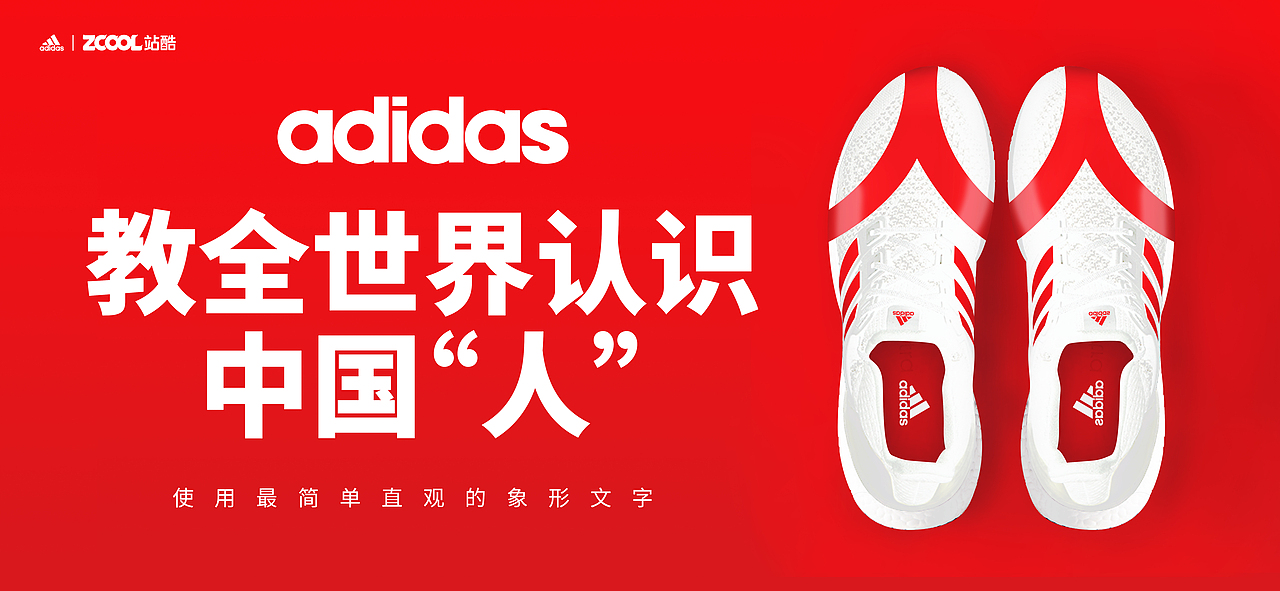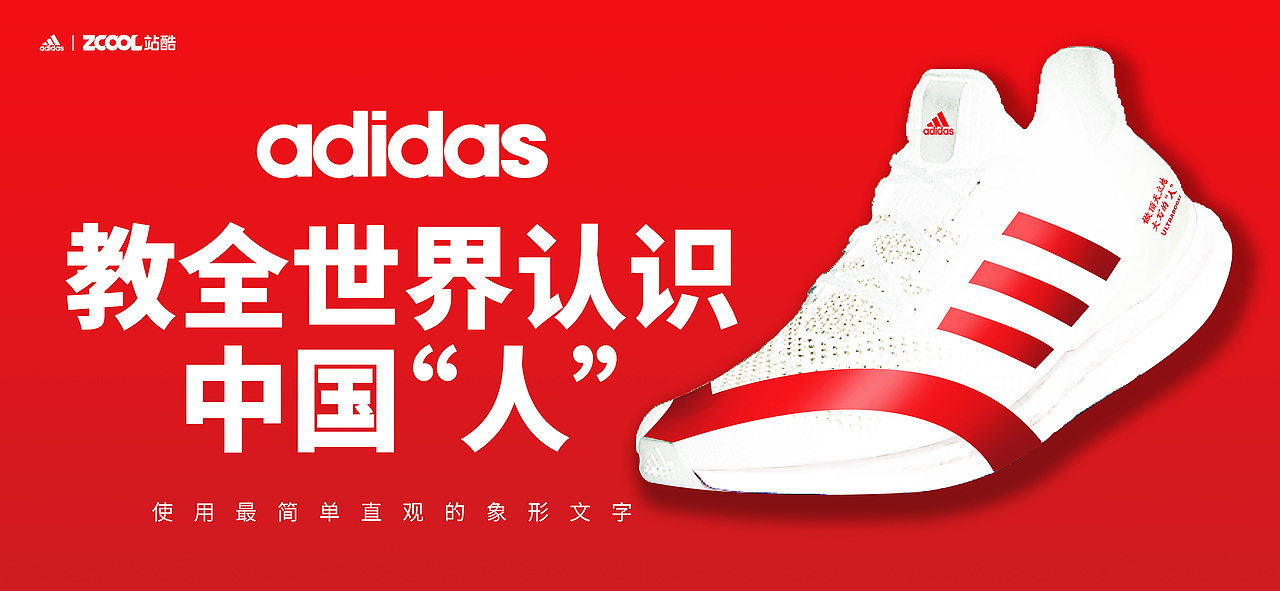
教全世界认识中国“人”
顺国潮,中国潮。在这个中国人当文化自信的年代,我之所以使用最简单直观的中国象形文字“人”为原型来设计这款鞋,是想教全世界认识中国“人”!这是我作为设计师一直的梦想,借着阿迪达斯给的这个难得的机会,我想让中国最古老的汉字,带给全世界人们,让世界人们认识中国文化。
做一个对社会有用的人,诚实守信的人。“人”字最简单。没有偏旁,没有繁体,但有一点是肯定的,大写的“人”脊梁是笔直的,人格是闪亮的,光就这两笔,就能支撑起一个像样的“人”字,大写的。这世界,就因为有了大写的人,才会充满希望和生机。大写,就是力量!做一个有用的人,不要做一个永远在一边为他人喝彩的人。做出自己,让别人来喝彩做一个有用的人,公公正正的写好“人”的一撇一捺。